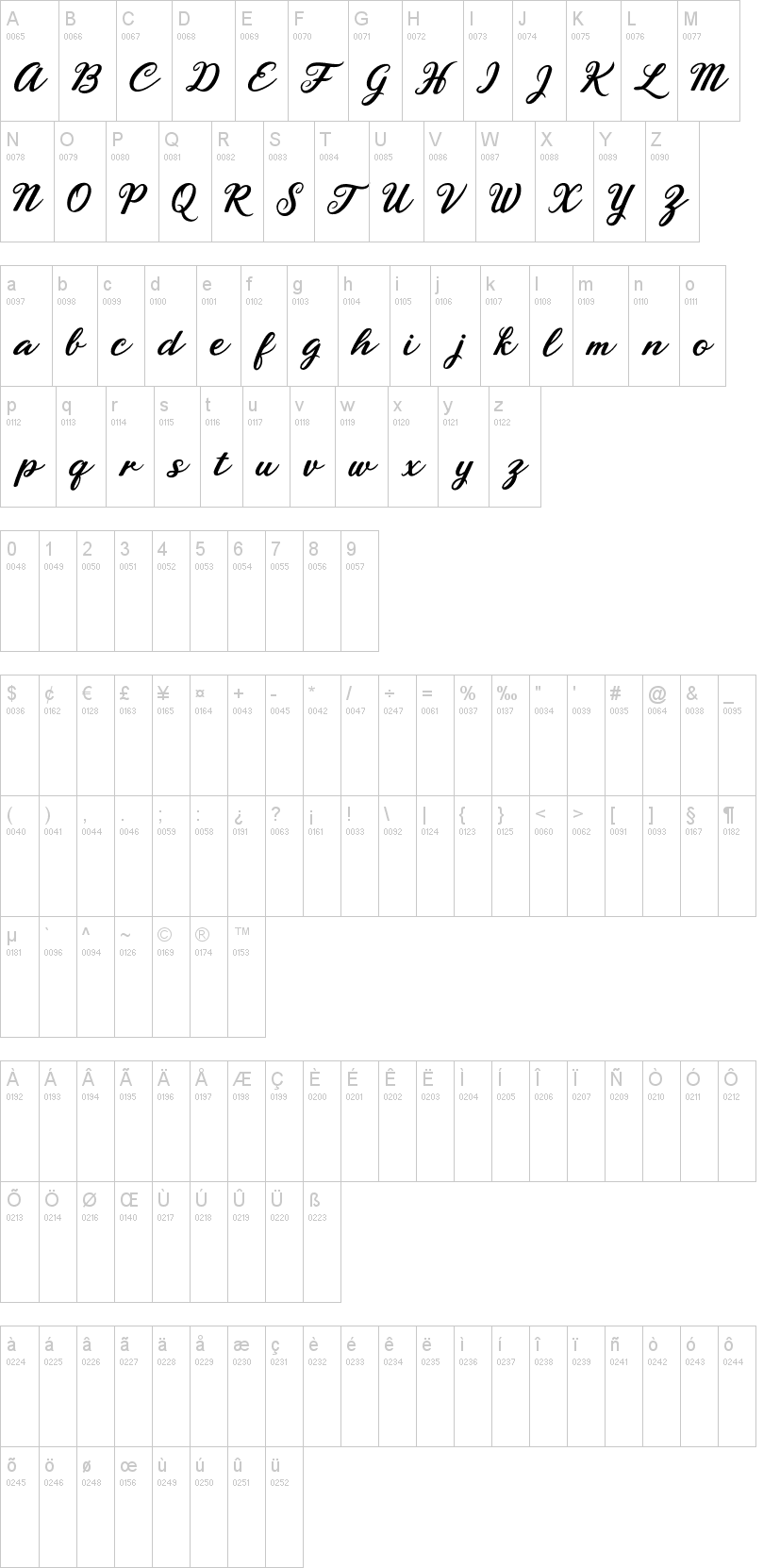
Rhyanie Lane
Rhyanie Lane 字体是一种自由曲线的手写字体,它具有自然、现代、温暖的特点,适合用于个性化的文字设计项目中。它的字体特征比较多变,包括圆润的笔画、大小不一的字母、不同的字母间距,以及自由流畅的设计。它可以用于各种设计项目,比如卡片,海报,标识,商业广告,书籍封面等等。
Rhyanie Lane是一款非常不错的手写艺术字体,具有很好的视觉感,适合于文化类的宣传设计、商业类品牌的广告和产品包装设计以及个性化文字排版等较多场景。
Rhyanie Lane字符映射图